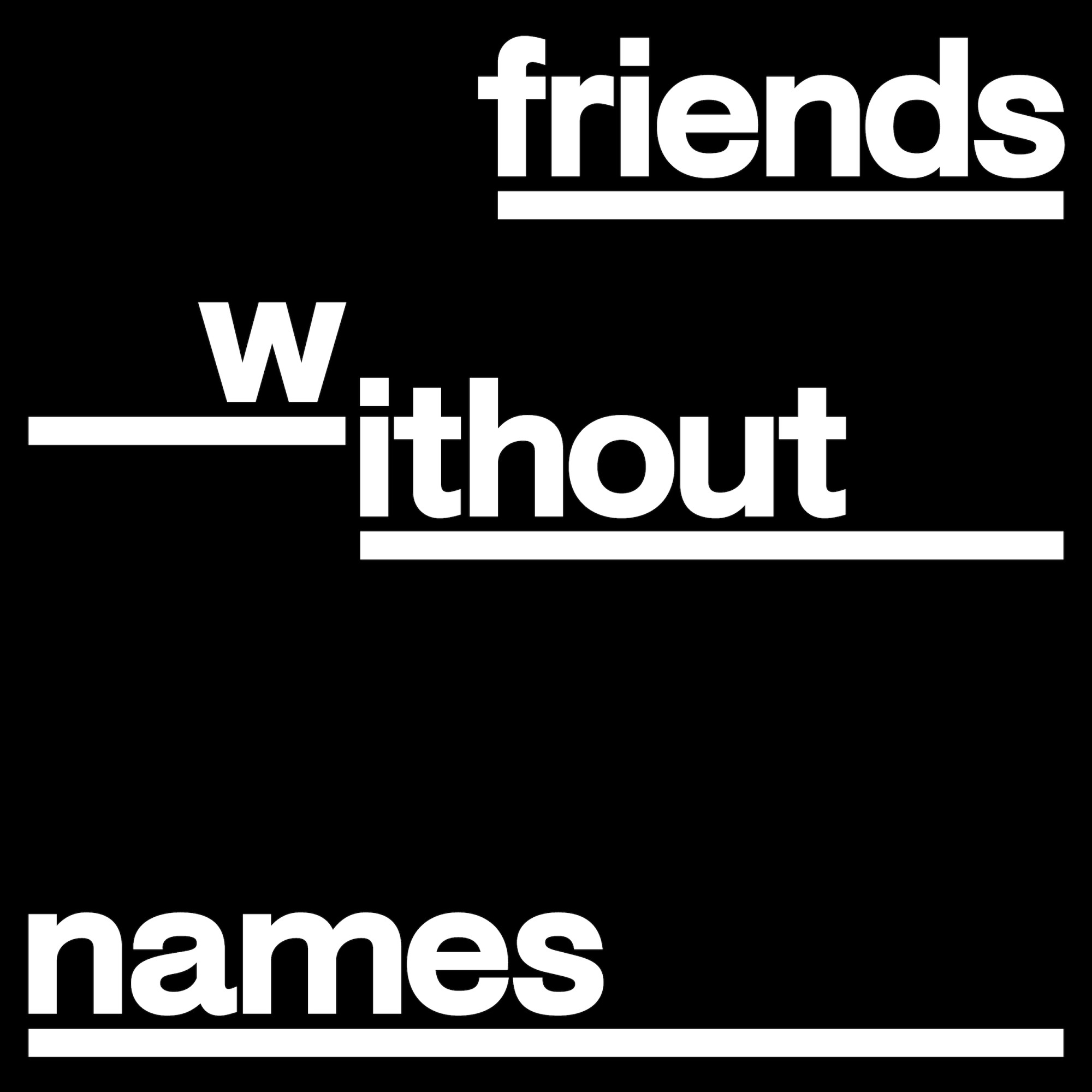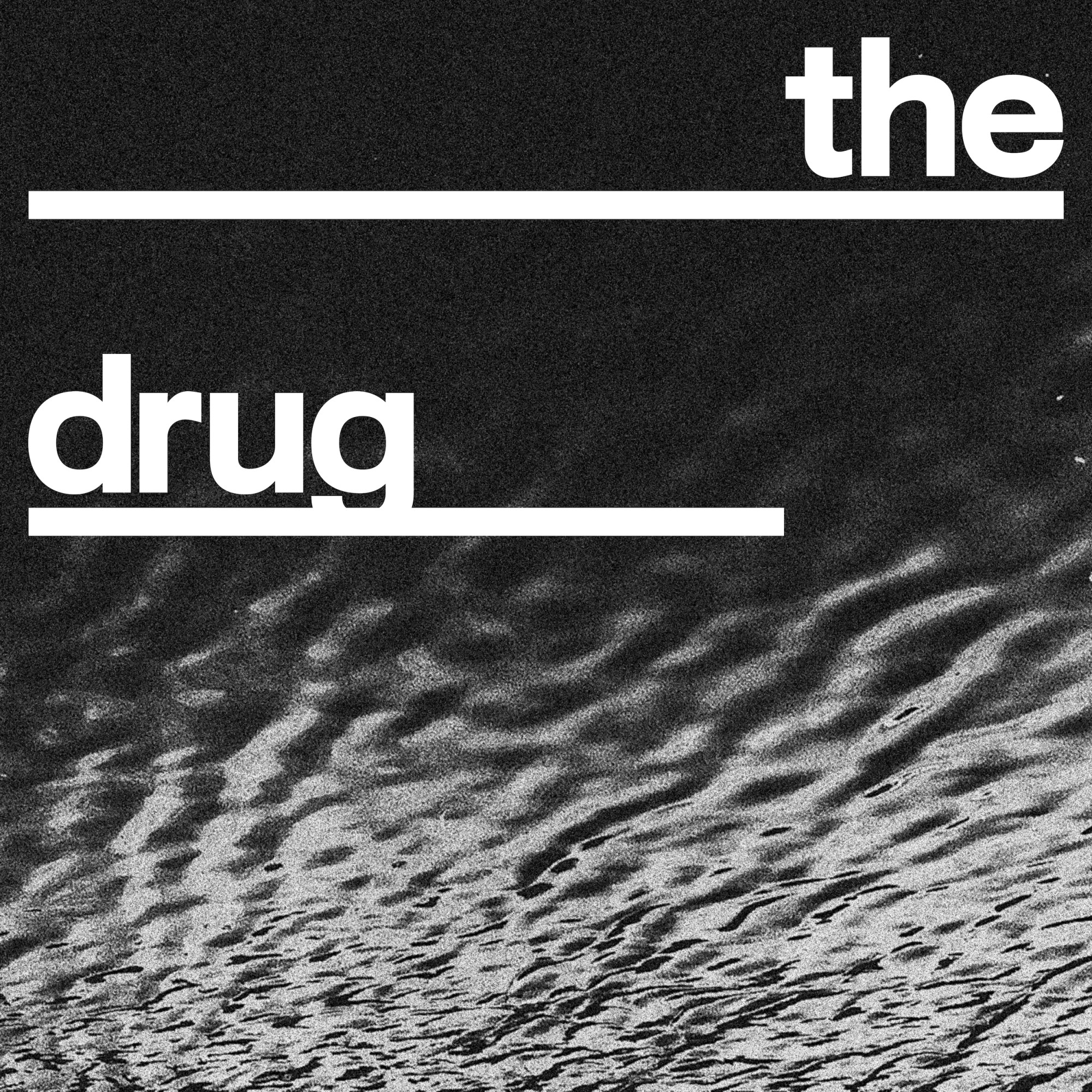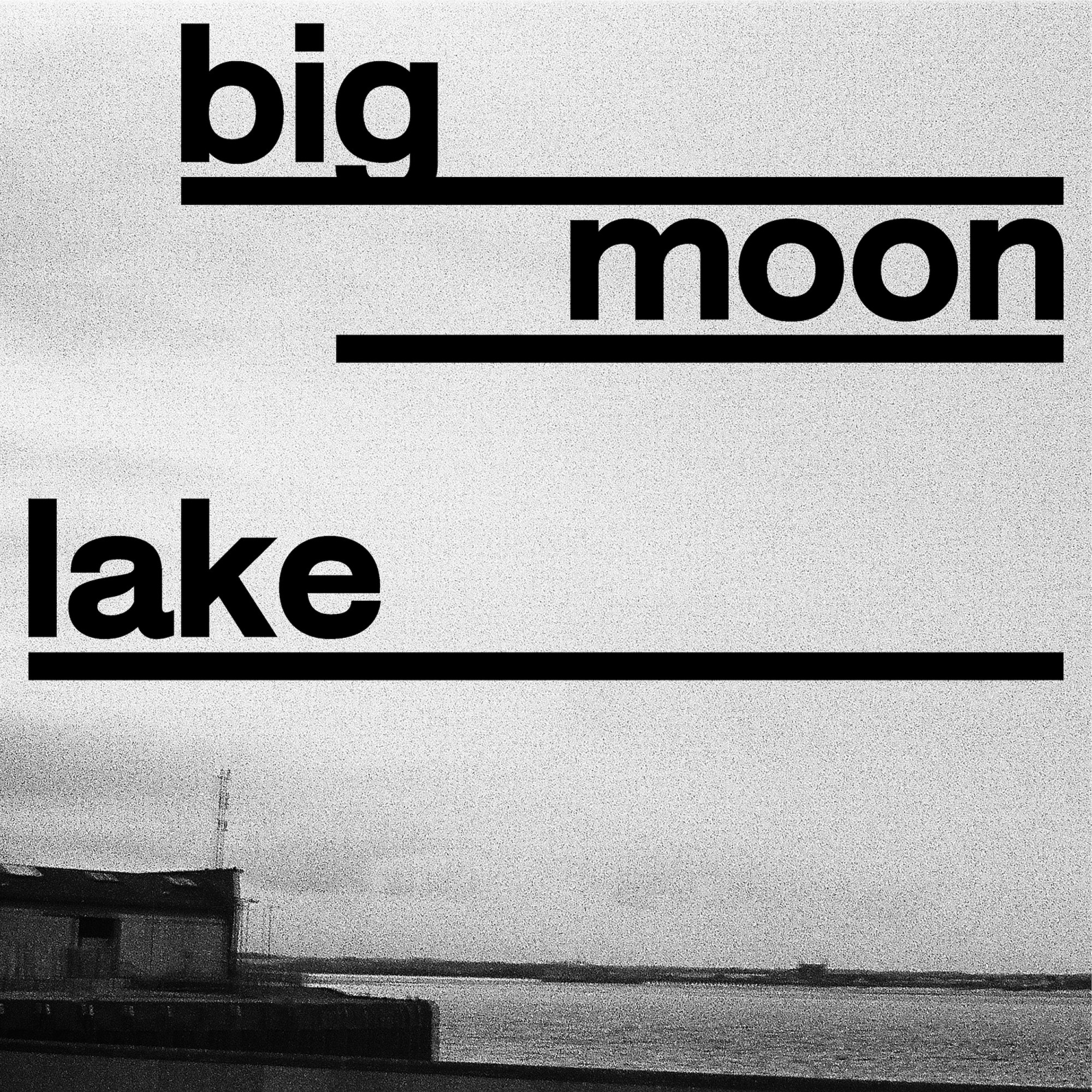
Verschiedene Singlecover
LIFE ist eine post-punk Band aus Hull, England.
Die Singles handeln musikalisch und textlich von Zugehörigkeit. Daher bilden rauhe schwarz-weiß Bilder von der Heimatstadt der Band die Grundlage der Single Cover. Zusätzlich werden die Namen der Singles versetzt angeordnet und verbildlichen so die Thematik.
Schrift: Default Sans von Scott Vander Zee